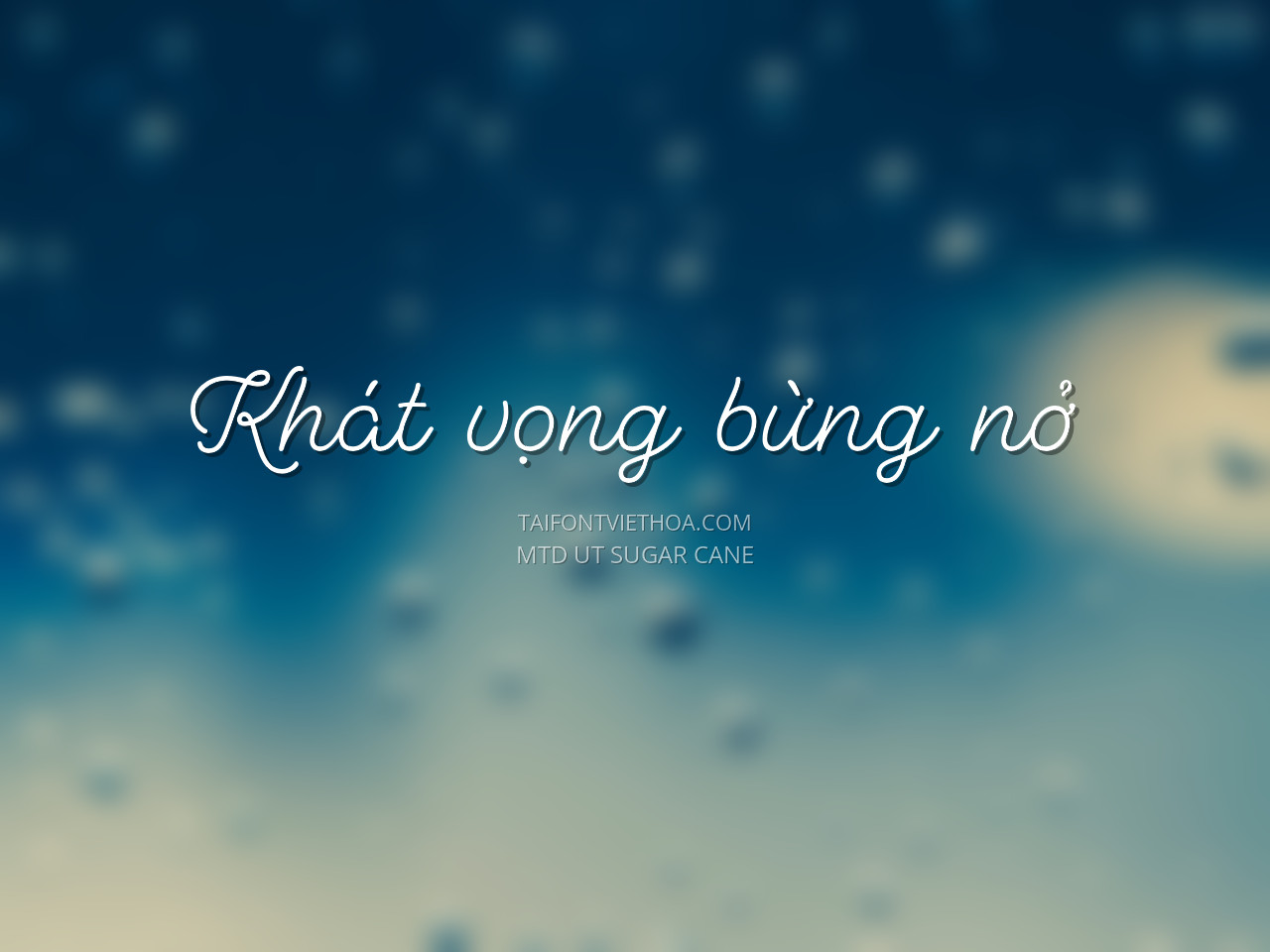
Font việt hóa MTD Ut Sugar Cane
Tác giả Font: Uniontype
Giới thiệu về font Ut Sugar Cane
Ut Sugar Cane là một font script đáng yêu mang phong cách handwritten, được phát triển bởi Motokiwo Type (MTD) phối hợp cùng UT Type – chuyên dòng font viết tay dễ thương, ngọt ngào và thân thiện. Font mô phỏng nét bút viết tay mềm mại, hơi nghiêng, mang lại cảm giác tinh nghịch và gần gũi, đặc biệt phù hợp với các thiết kế dành cho trẻ em, thương hiệu nữ tính hoặc sản phẩm thủ công. Phiên bản Việt hóa do MTD thực hiện đầy đủ, hỗ trợ trọn bộ ký tự tiếng Việt và hơn 60 ngôn ngữ quốc tế khác.
Đặc điểm thiết kế và ứng dụng của font Ut Sugar Cane
Font sở hữu nét chữ bo tròn, mềm mại với các đường cong tự nhiên, tạo cảm giác nhẹ nhàng và dễ tiếp cận. Swashes ở chữ cái đầu hoặc cuối giúp tăng tính trang trí, trong khi các chữ thường vẫn giữ được sự đơn giản và rõ ràng. Cấu trúc chữ nhất quán giúp font hoạt động tốt ở nhiều kích thước khác nhau, từ tiêu đề lớn đến văn bản in trên nhãn mác nhỏ.
Ut Sugar Cane rất phù hợp với các thiết kế như: sản phẩm dành cho trẻ em, bao bì quà tặng, thương hiệu handmade, sticker, blog, poster truyền cảm hứng hoặc các chiến dịch quảng cáo mạng xã hội thân thiện. Ngành nghề phù hợp gồm: giáo dục, ẩm thực, sản phẩm handmade, quà tặng, thời trang trẻ, spa và thương hiệu nữ tính.